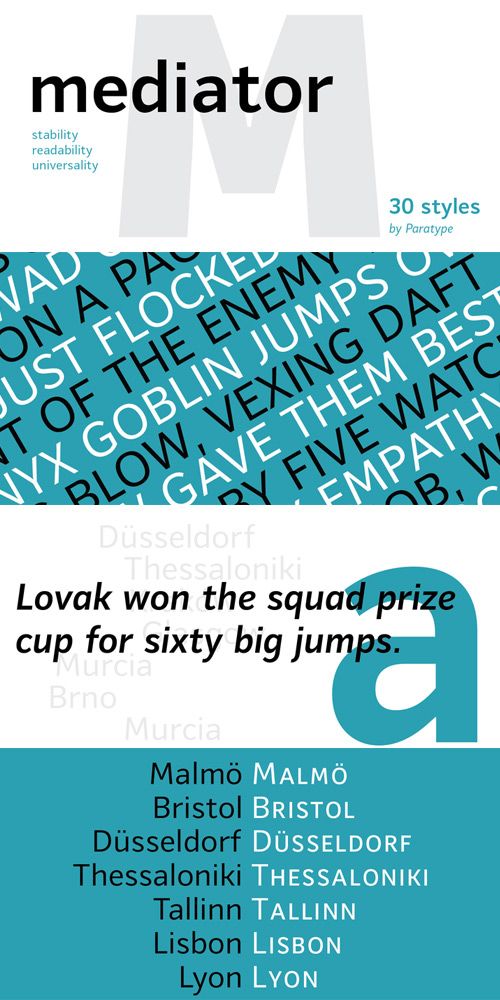
Mediator - шрифт
Mediator является сбалансированным современным шрифтом без засечек, который выполнен также и в размерах дисплея и основного текста. Семейство содержит 30 шрифтов в 3 ширины: 8 романс с соответствующими курсивом, слегка расширенных пропорций, от тонких до черного; 7 узкие и 7 конденсируется, от тонких до ExtraBol
Шрифт поддерживает русский язык
А кириллица есть, очень хорошая